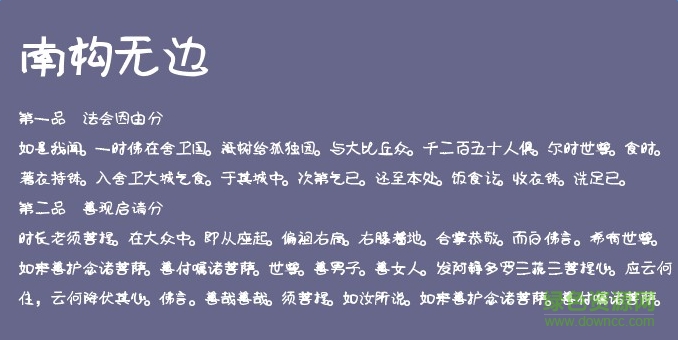
南構無邊字體是一款字庫完整的葉根友南構字體,字體線條粗細均勻,筆畫清晰而隨意,結構勻稱美觀,字形灑脫優(yōu)雅,應用效果非常好,喜歡的朋友歡迎在綠色資源網下載!
南構無邊字體是一款風格獨特的字體,該字體擁有中文漢字6763個,字形菱角分明,筆畫錯落有致,藝術感強,能夠適用于產品包裝、廣告宣傳、出版印刷、商標用字、商業(yè)網站、影視影像視頻、書籍出版印刷等,有需要的朋友可以免費下載收藏。